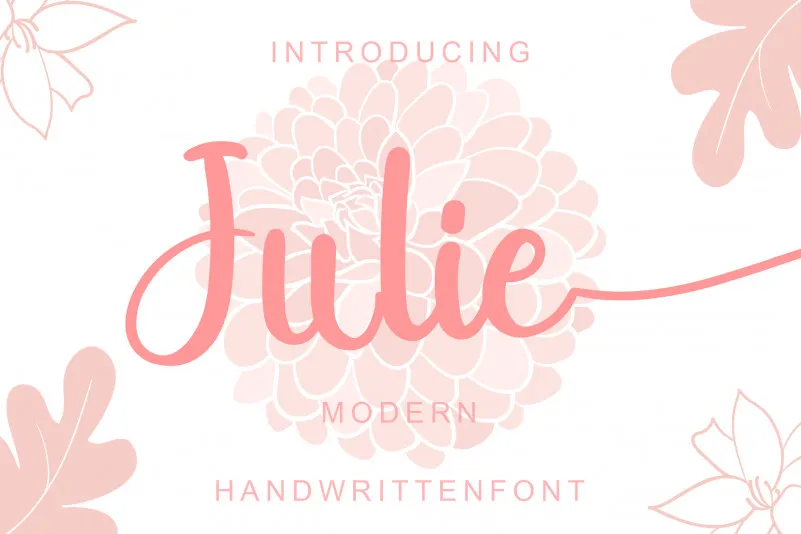
Julie Font – Download Grátis
A Julie Font é uma elegante fuente de script que brilha em qualquer projeto visual. Seja para criar cartões de agradecimento, convites de casamento ou logotipos personalizados, ela oferece um toque único e sofisticado. Com sua codificação PUA (Uniforme Personalizada de Accessibilidade), é fácil acessar todos os símbolos e traços alternativos desta fuente única. Ideal tanto para projetos pessoais quanto corporativos, a Julie se destaca em qualquer design que busque uma personalização perfeita.
Designer: Genarastudio